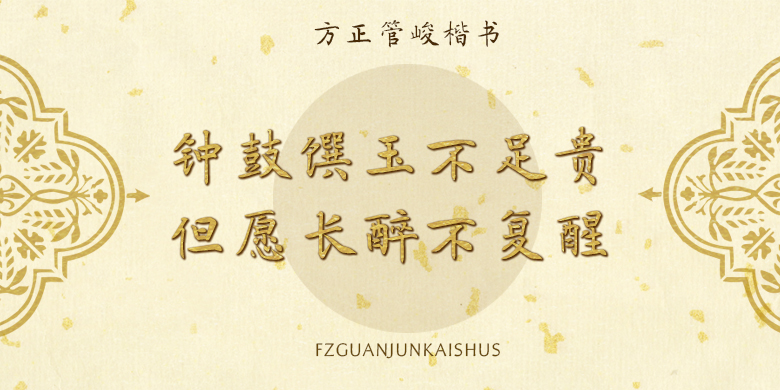
方正管峻楷书
方正管峻楷书,这款字体结构工整、笔画清晰,兼顾美观与易读性,适用于标题、正文、海报、包装、LOGO 等多种场景。字形优雅稳定,风格百搭耐看,适配日常排版与创意设计,让文字呈现更舒适、更具质感。方正管峻楷书一笔一画,皆是细节,以均衡的比例、流畅的线条打造舒适视觉体验,字形端正大气,风格简约现代。无论是商业设计、品牌宣传还是日常排版,都能轻松驾驭,让文字更有格调与力量。方正管峻楷书字体下载。
管峻楷书由当代书法家管峻先生创作。这款字体用笔细劲又多轻重对比,轻巧自然,结体以褚遂良书法为本,参以己意自成一家,工稳清丽。其风格秀美空灵,适用于文化类的宣传设计,以及商业类品牌的广告和产品包装设计。